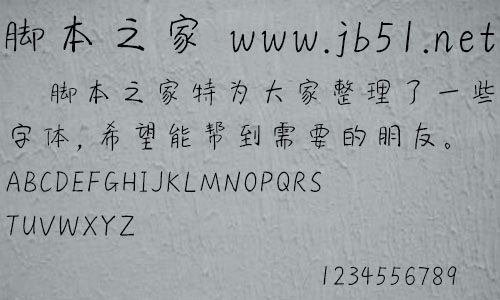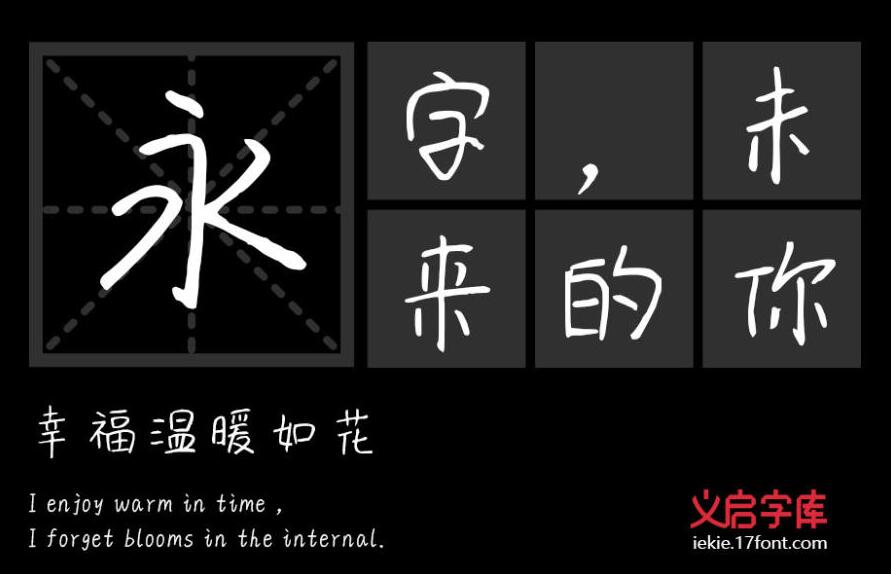
義啟寬窄巷子小酒館一款不錯(cuò)的藝術(shù)字體,由義啟字庫(kù)出品,字體筆觸纖細(xì),書(shū)寫(xiě)流暢灑脫,適合應(yīng)用于藝術(shù)設(shè)計(jì)、平面宣傳設(shè)計(jì)、網(wǎng)頁(yè)設(shè)計(jì),書(shū)法字帖等領(lǐng)域,需要的朋友可以前來(lái)本站下載。